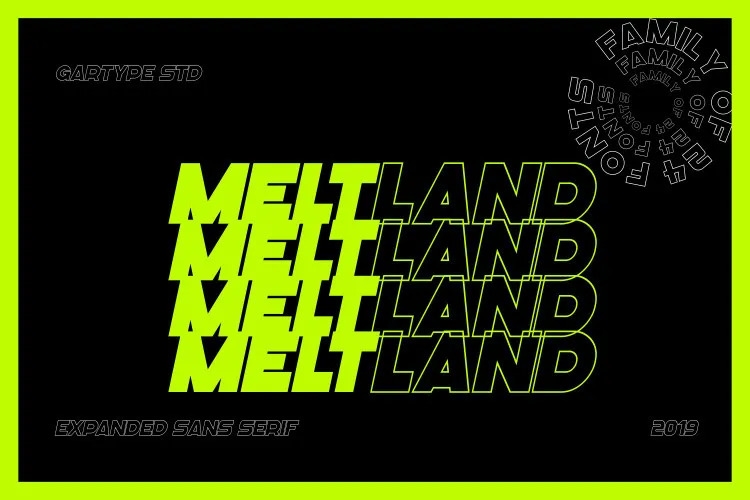
Meltland Sans Serif Font é uma escolha inovadora para designers que buscam um estilo único e forte. Sua família de 24 tipos de fontes inclui uma itálica desbotada com força e feroz, criando um arrespejado contraste entre o suave e o robusto. Este é um pacote de fontes criadas manualmente pela Gartype Studio que oferece versatilidade, permitindo a criação de títulos de embalagens, revistas, ótimas frases, itens imprimíveis, mídia e design de marca criativo. Sua rica história de design o torna uma escolha inteligente para qualquer projeto que busque destaque ou impacto visual em sua apresentação. Engajue-se no universo de criação com Meltland Sans Serif Font – seu novo aliado de design!